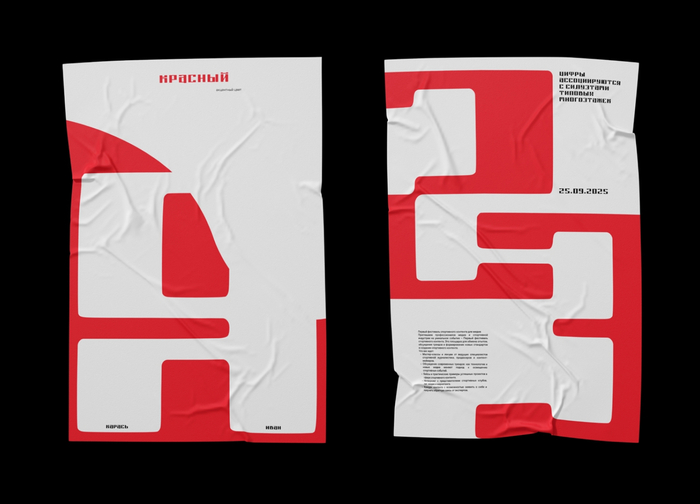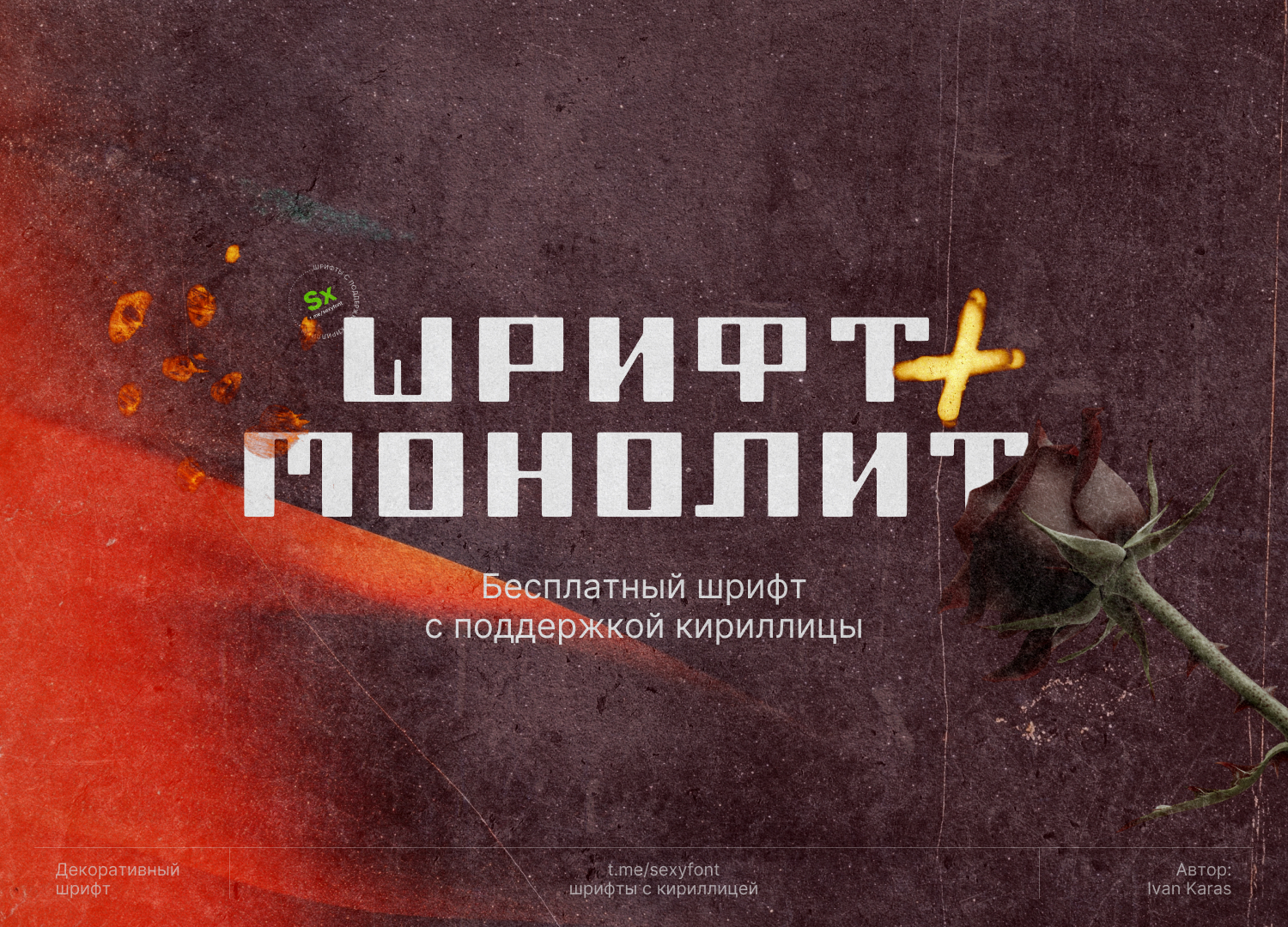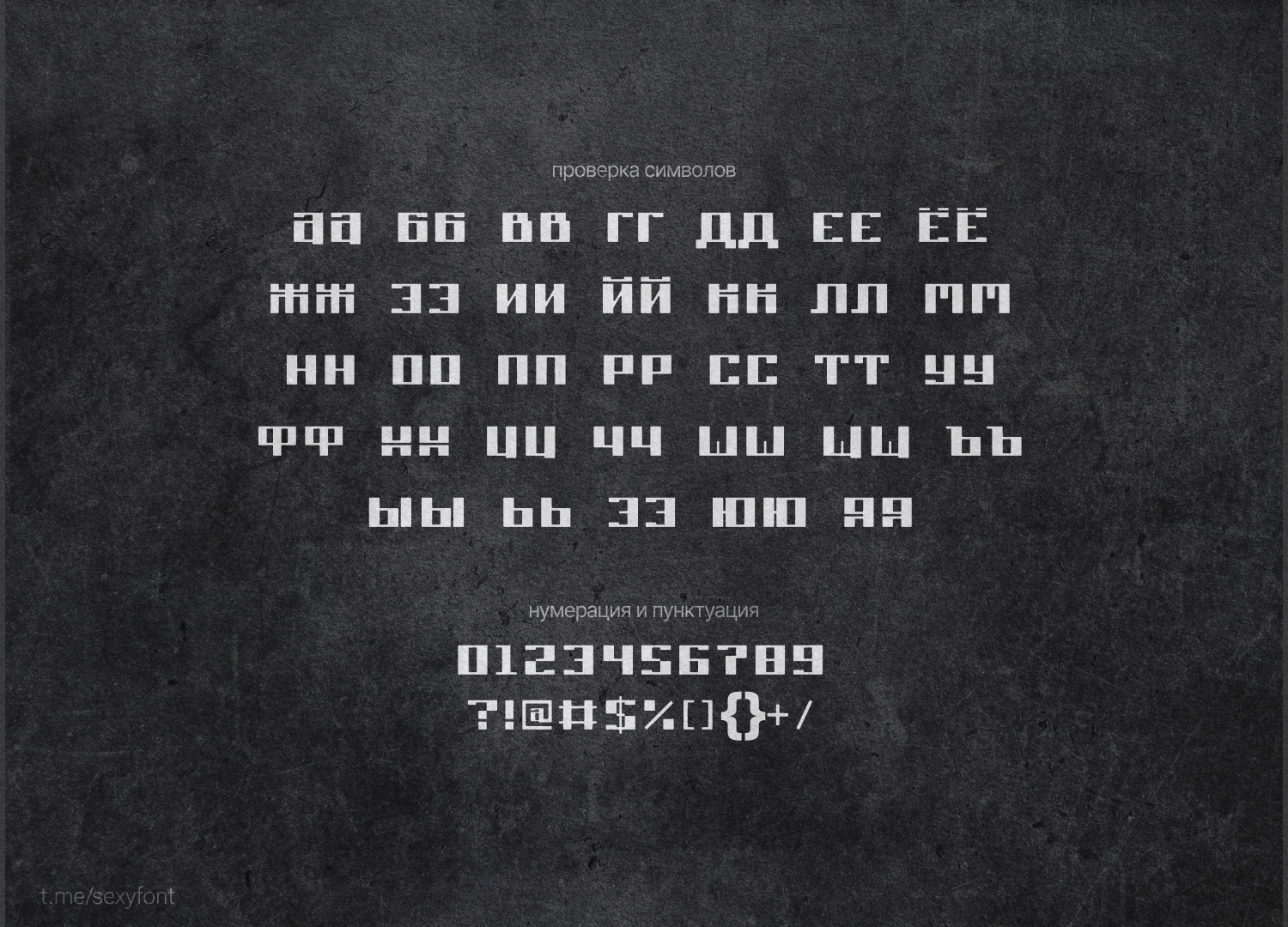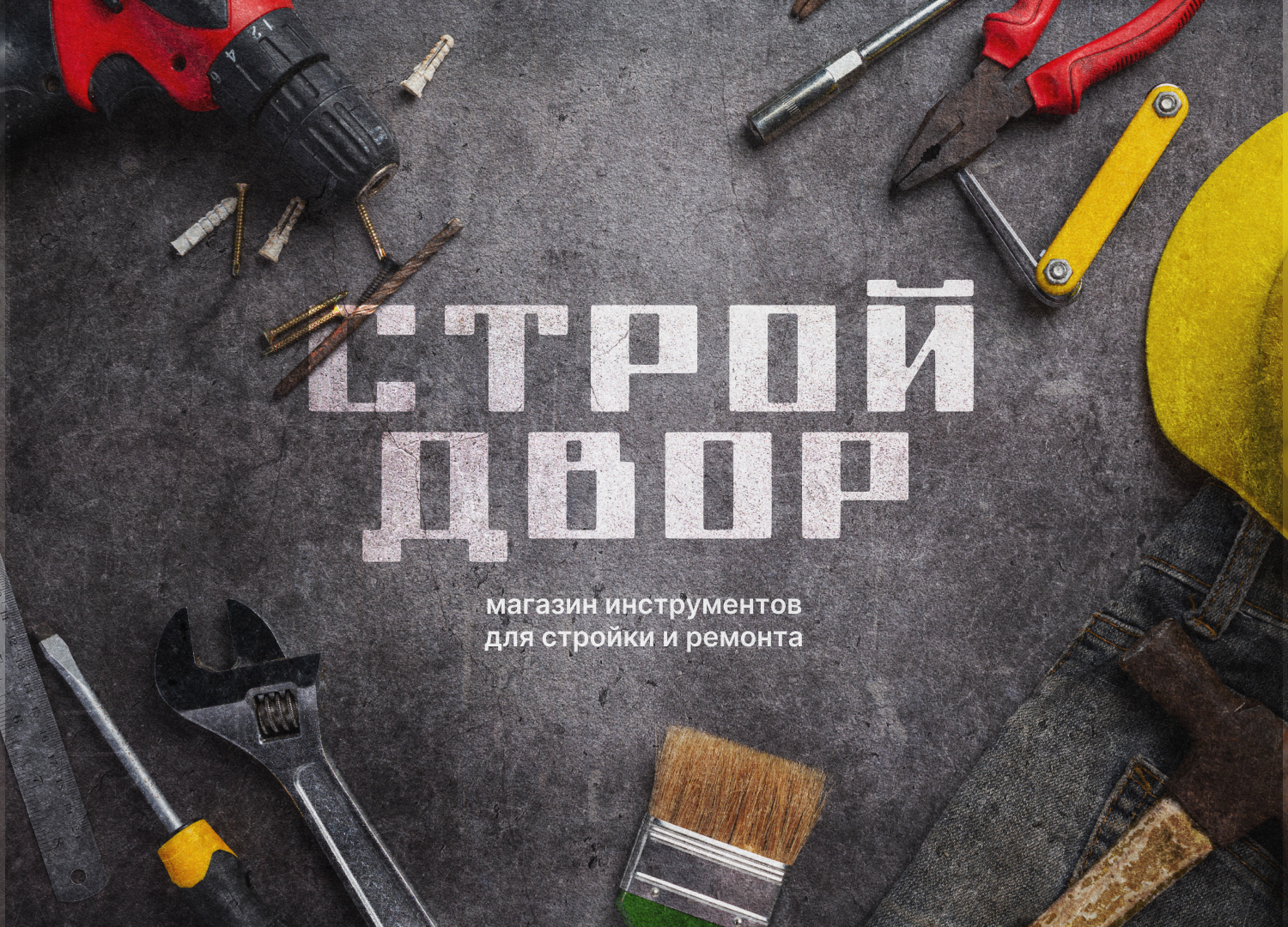
Шрифт Монолит
Шрифт Монолит — акцидентный гротеск с характером, сочетающий архитектурную строгость форм и глубокую культурную отсылку. Основой дизайна стали графемы, вдохновленные уставным письмом русского языка, что придает шрифту монументальность и устойчивость. Геометрическая четкость букв гармонично соседствует с элементами, отсылающими к типографским традициям Советского Союза
Автор: Иван Карась